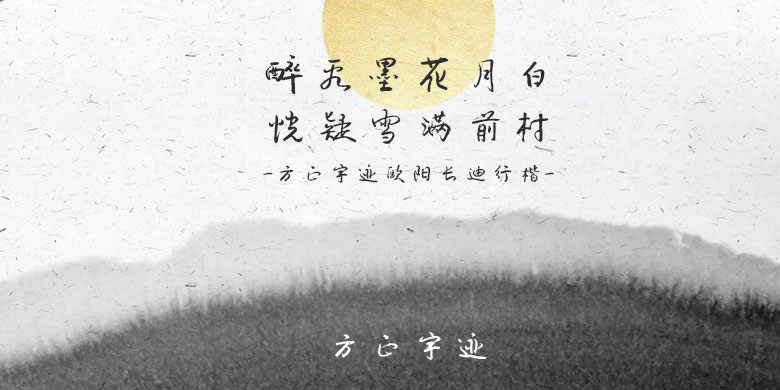
品牌:方正字迹设计师:欧阳长迪发行时间:2019字库编码:大陆简体(GB2312-80)分类:常规书写·毛笔字体属性:精品字
欧阳长迪行楷是一款传统的行书字体,该款字体遒劲有力,舒展大方,借鉴吸收了王羲之行书的特点,融入了楷书的端正大方,是一种用途十分广泛的书法字体。适用于文化类、广告类、屏显及彩页的宣传设计,以及商业类设计等。